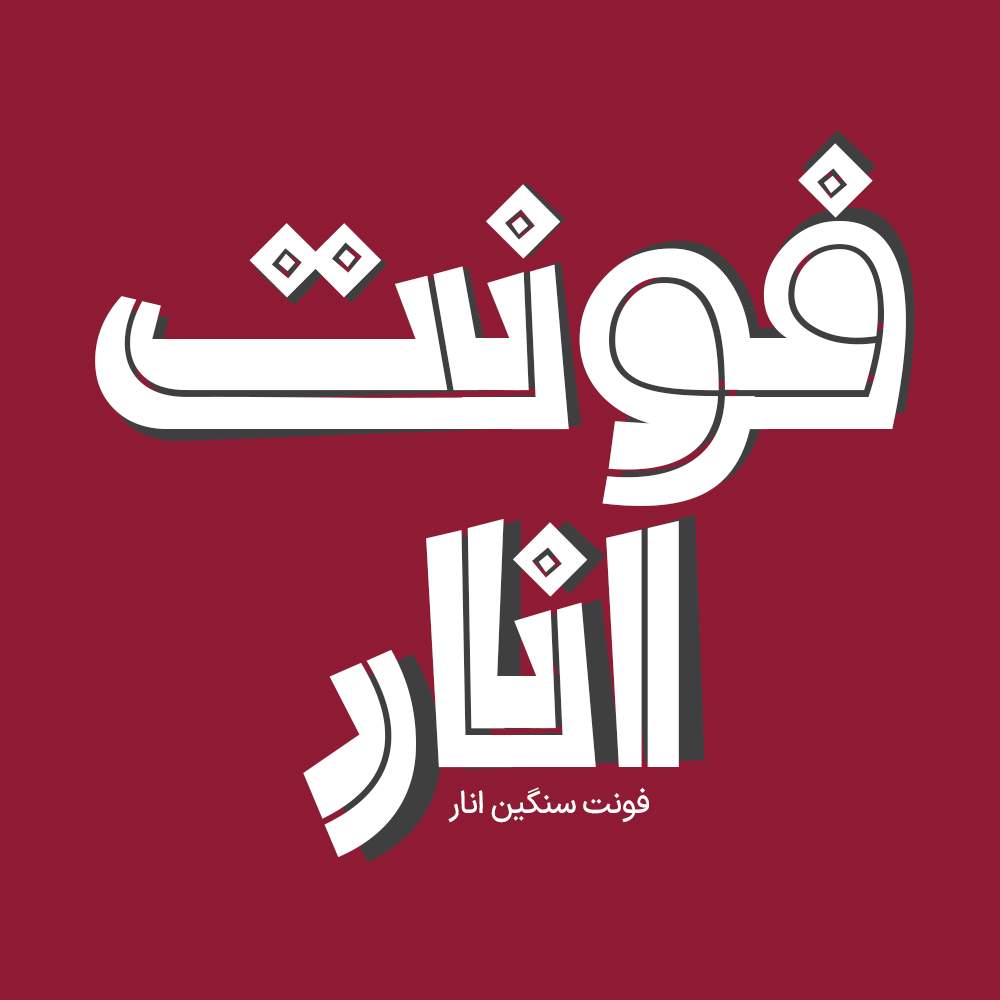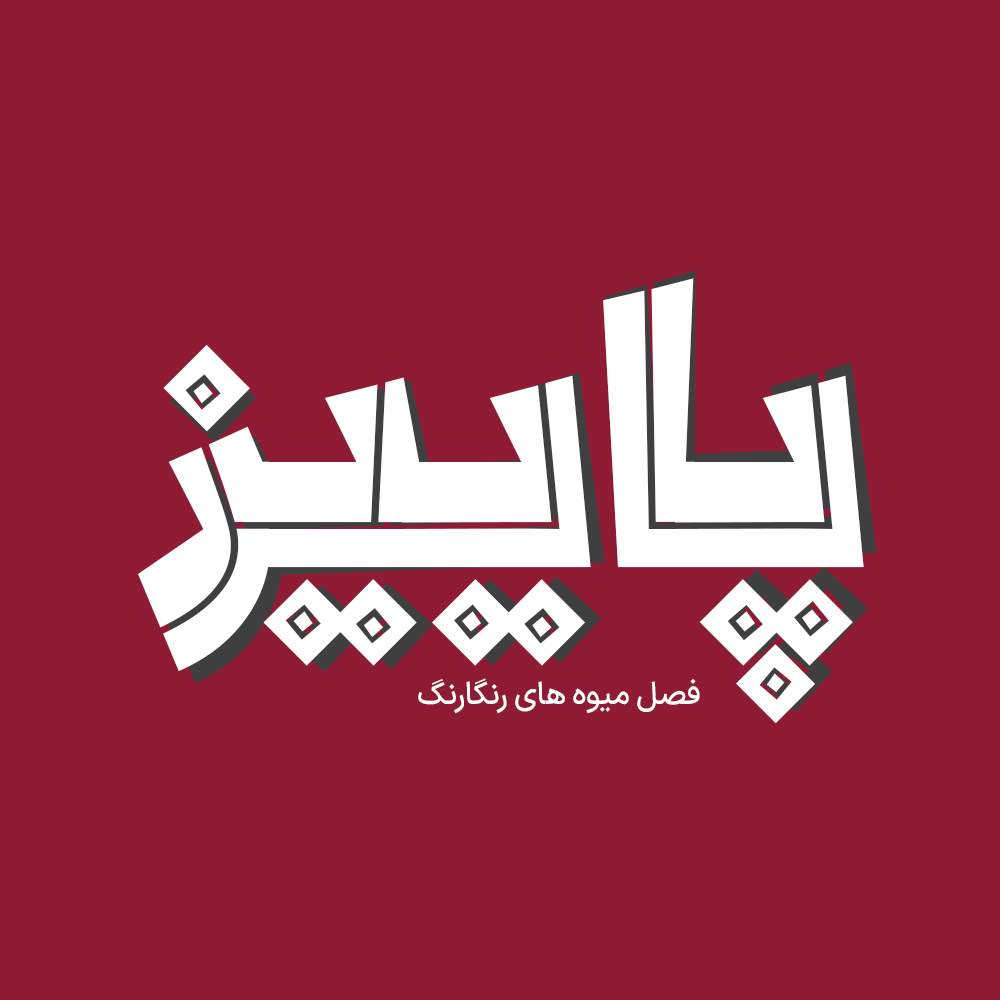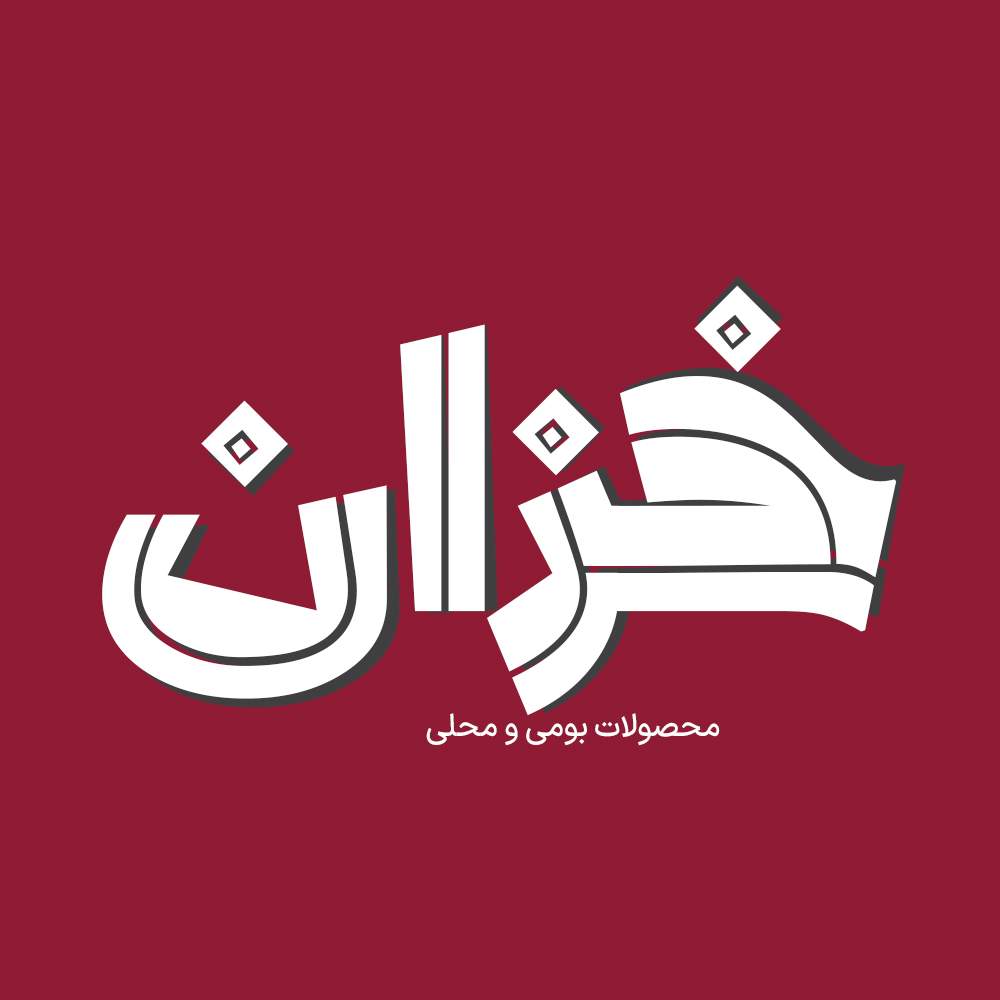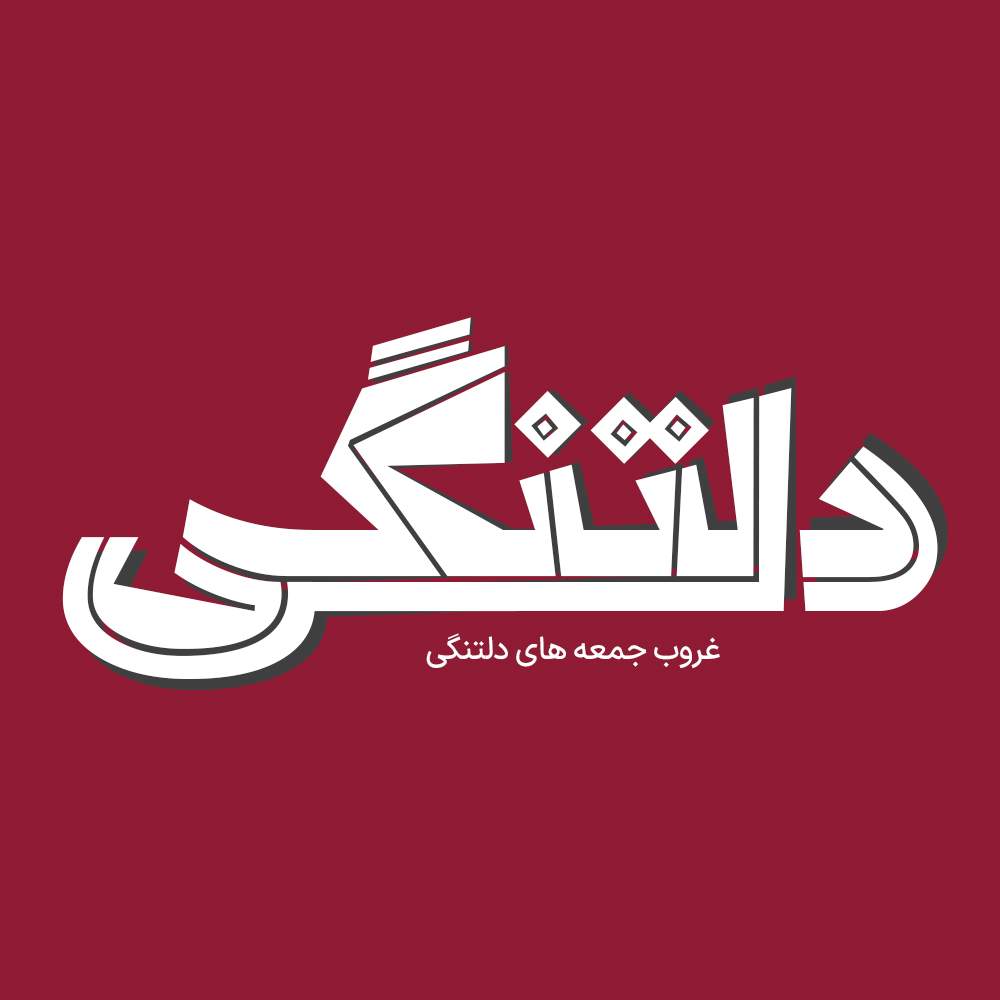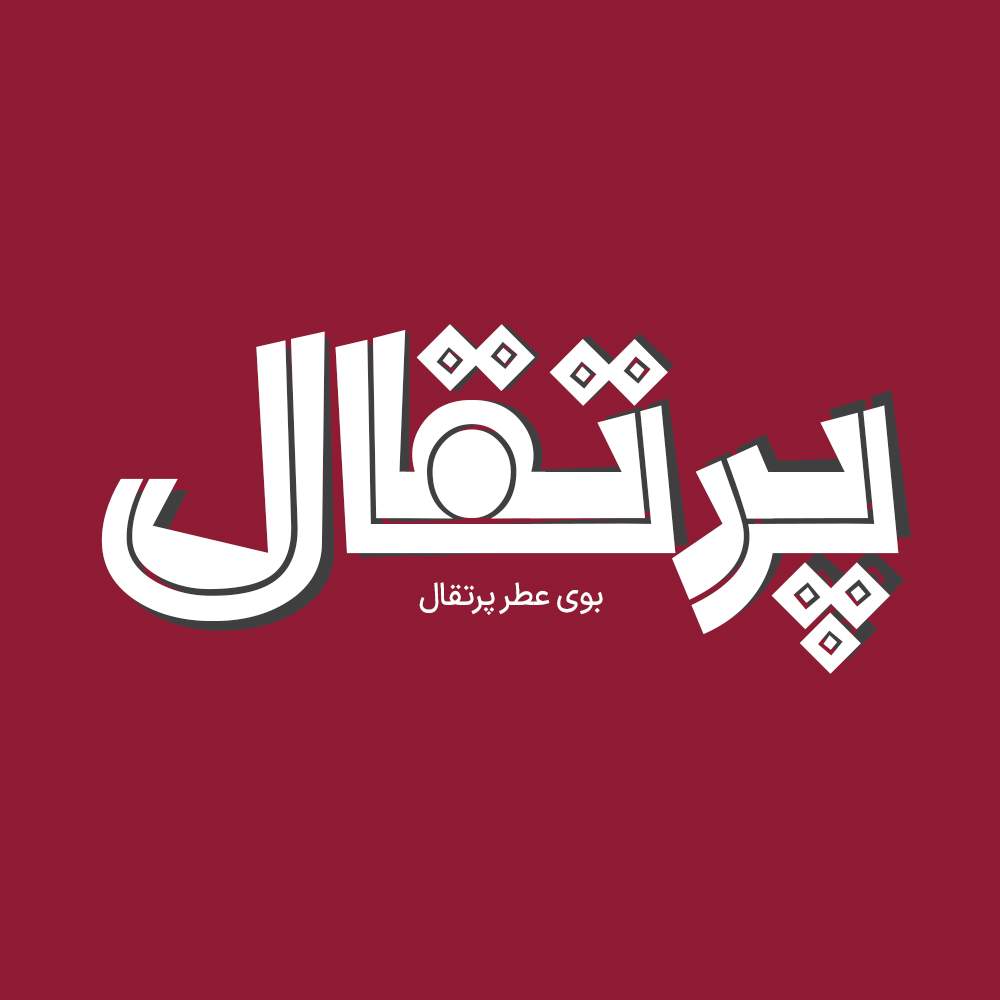
فونت فارسی انار Anar Font
فونت فارسی انار یک فونت متفاوت و زیبای فارسی می باشد که در وزن سنگین طراحی شده است، فونت فارسی انار مناسب استفاده در عناوین و…
فونت فارسی انار یک فونت متفاوت و زیبای فارسی می باشد که در وزن سنگین طراحی شده است، فونت فارسی انار مناسب استفاده در عناوین و تیترها هم طراحی انواع لوگوتایپ، تکست گرافی و استفاده در طراحی های خاص می باشد.
پیشنمایش و نمونه تایپ های فونت انار